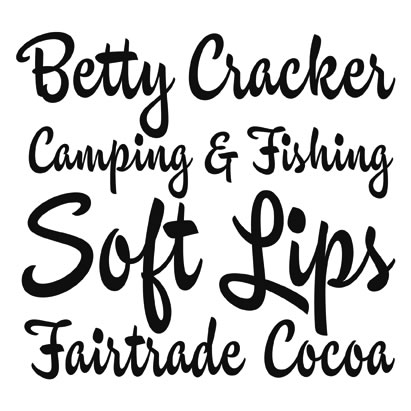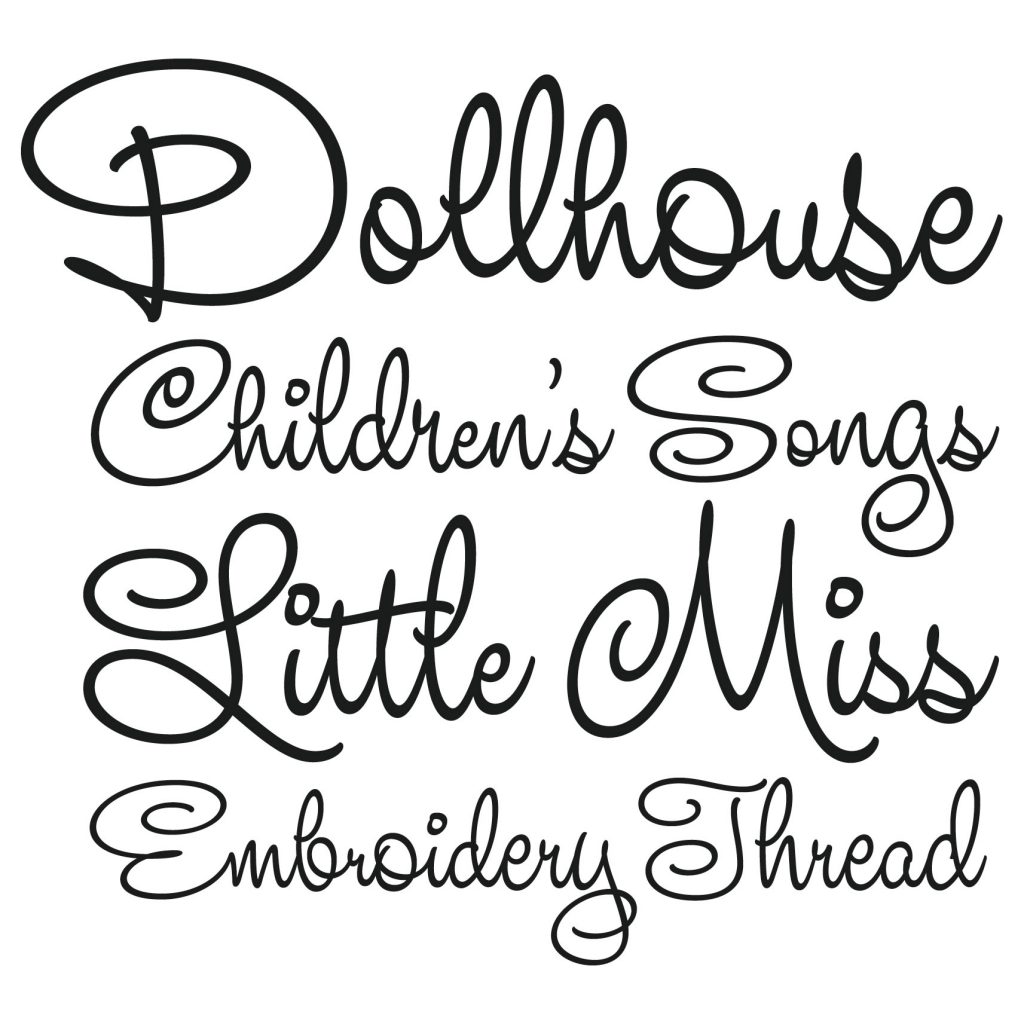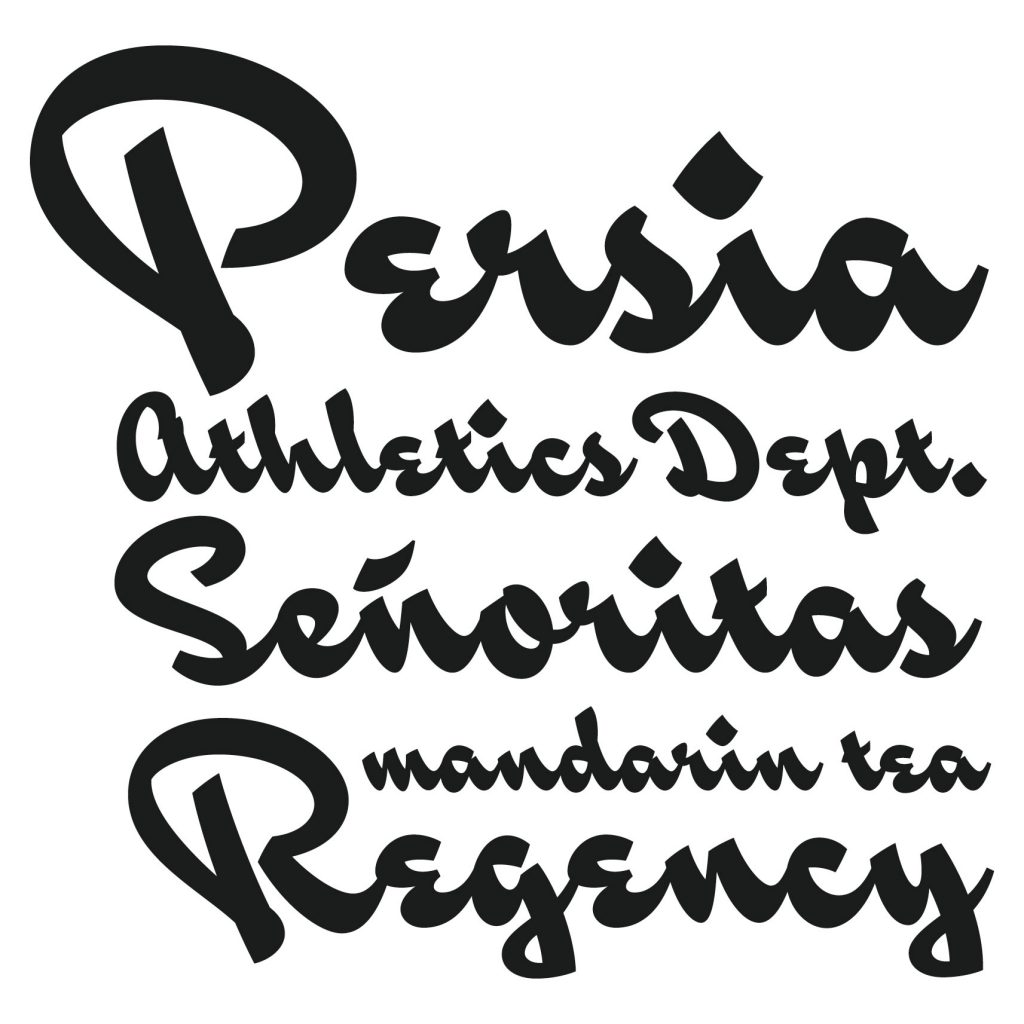
Hablar de House Industries y del impacto que este estudio especializado en el diseño de fuentes ha causado en nuestra profesión, es hablar de una carrera llena de éxitos comerciales y de multitud de premios concedidos por organizaciones, empresas y asociaciones de todo el mundo.
Esta empresa americana, fundada en 1993 por Andy Cruz y Rich Roat como Brand Design Co. en el trastero del apartamento de éste último, supo canalizar de manera muy inteligente su ferviente pasión e influencia hacia la estética gráfica de mediados de siglo XX. Toda una serie de fuentes frescas, divertidas y de una calidad excelente, apoyadas por unos elementos de promoción que hicieron las delicias de todo profesional amante de la tipografía, provocaron con el tiempo, que no hubiera una agencia de publicidad o estudio de diseño que se acabara rindiendo a sus encantos y comprara alguna tipografía diseñada por ellos.
Ken Barber se unió a House Industries en 1996. Su entusiasmo por la caligrafía americana de los años 60 y 70 y su gran capacidad productiva en el diseño y desarrollo de nuevas fuentes, le han convertido en una pieza clave dentro de la empresa.
UnosTiposduros ha hablado con él para conocer un poco más al detalle qué es House y cuál es su particular visión de la tipografía.
¿Me podrías explicar de forma breve quien eres y qué representa House Industries?
House Industries es una fundición tipográfica con base en Delaware (Yorklyn) especializada en el diseño de fuentes digitales, pero también funcionamos y trabajamos como cualquier estudio de diseño gráfico en general. De hecho, además de ser calígrafo y diseñador de tipos, también soy el director de desarrollo tipográfico de la compañía.
¿Cuándo arrancáis un nuevo proyecto, cuál es vuestro proceso de trabajo y a qué le dais mayor importancia?
Cuando empezamos un nuevo proyecto tipográfico, es importante para nosotros considerar varios factores. Primero: el tema del proyecto debe satisfacernos personalmente; esto significa que tanto la base, el guión, como los objetivos del nuevo proyecto debe estimularnos lo suficiente como para justificar el tiempo y el esfuerzo necesarios para producirlo.
Segundo: necesitamos evaluar si nuestros consumidores van a estar o no interesados en nuestras nuevas propuestas tipografías y en todos los productos relacionados. Obviamente, este nuevo proyecto debe diferenciarse claramente de los otros productos que ofrecemos.
Luego empezamos a estudiar y desarrollar las fuentes mientras visualizamos posibles productos que conecten con el tema del proyecto. Después de probar rigurosamente los tipos y los accesorios hacemos material de marketing para hacer publicidad del producto final.
¿Todos los proyectos de House Industries se desarrollan de forma colectiva o bien os gusta trabajar individualmente?
Todos los proyectos de House Industries son producto de un esfuerzo colectivo. Mientras no todo el mundo está involucrado con todos los proyectos particulares, el proceso creativo, sin embargo, sigue siendo muy colaborativo.
Vuestras tipografías respiran una gran admiración por los estilos gráficos de los años 60 y 70. ¿Qué es lo que tanto os apasiona de esa época?
Durante varias décadas pasadas ha habido un declive en el uso del diseño tradicional y en las técnicas de ilustración que generalmente eran usadas durante la mayor parte del siglo XX. Por consiguiente, la artesanía parece ausente en muchos de los diseños gráficos contemporáneos.
House está interesada simplemente en investigar y perpetuar éstas prácticas tradicionales, incorporándolas a nuestro trabajo.
Todos vuestros productos tienen una cuidada presentación gráfica, le dais mucha importancia a los detalles… Y eso también ocurre en todos los materiales promocionales producidos por House (catálogos, vuestro libro, la ropa…)
Trabajar en el diseño de fuentes durante meses puede llegar a ser algo completamente aburrido. Diseñando catálogos que nos comporten ciertas complicaciones o riesgos y presentando soluciones gráficas a esas complicaciones (incluso aplicando esas premisas al diseño de ropa), nos da la oportunidad para escapar de la rutina diaria de puntos y píxeles alrededor de la pantalla de un ordenador.
También es vital para House Industries que cada elemento de todos los proyectos reciba la misma cantidad de atención que nosotros estamos acostumbrados a poner en todos los trabajos.
Y por último, los consumidores, al fin y al cabo, se benefician consiguiendo algo más que una fuente o una camiseta: de hecho, uno de nuestros máximos objetivos es experimentar con el diseño gráfico de forma que el cliente final disfrute de la parte práctica.
Una de las propuestas más interesantes de House Industries es la “tematización” de vuestras tipografías. ¿Como surgió esta idea de no diseñar fuentes de forma independiente sino crear packs con una línea argumental concreta?
Andy Cruz, co-fundador de House Industries, fue el que introdujo la idea de hacer publicidad colectiva con nuestras fuentes a través de embalajes temáticamente relacionados. Anteriomente, la mayoría de los fabricantes de tipos y sus respectivos distribuidores, estuvieron vendiendo fuentes o familias de tipos de forma individual.
Nosotros ampliamos esta idea agrupando fuentes estilísticamente definidas y vendiéndolas como un producto individual.
También, de una manera sutil, se nos presentaba una buena excusa para hacer algún embalaje “cool” y de paso informar a nuestros consumidores sobre artistas y géneros del diseño poco valorados, que de otra manera, ellos nunca hubieran llegado a conocer.
Actualmente hay una proliferación enorme de pequeñas fundiciones gracias a la tecnología digital. Algunas de estas fundiciones tienen una gran calidad en sus trabajos.
¿Sigues o te gusta alguna en concreto?
Personalmente, me alegra mucho ver nuevos diseñadores de tipos y nuevas fundiciones ofreciéndonos diseños de fuentes de calidad.
En nuestro país, desgraciadamente, el pirateo tipográfico está a la orden del día. ¿Cual crees que puede ser la causa y lo más importante, cual podría ser la solución para disminuir este problema?
La solución puede empezar por los diseñadores gráficos profesionales. Los usuarios de las fuentes deberían ofrecer a los diseñadores tipográficos el mismo respeto que esperan para ellos. La piratería no sólo devalúa el diseño de tipos sino que también devalúa el diseño gráfico en general. Debido a esto, ha provocado que el diseñador gráfico pierda respeto por parte del público no profesional y a consecuencia de ello, prácticamente todo el mundo tenga una imagen mas o menos distorsionada de lo que es actualmente un diseñador gráfico. Nosotros, como profesionales, debemos trabajar para promover y cuidar ese respeto.
Creo que esta base puede ser un ejemplo para el público en general y puede servir para que haya un cambio de actitud tanto para el diseñador gráfico como para los profesiones de diseño de tipos.
Vuestro nuevo proyecto se llama Studio Lettering. ¿Puedes hablarme un poco de él?
Studio Lettering comprende una colección de tres tipos de letras de estilo Script y una fuente de símbolos inspirada en la publicidad caligráfica de mitad del siglo XX. Estas tipografías exploran los diferentes matices estilísticos característicos de la época que las hacen particulares en ciertos lenguajes y culturas.
Las características “coloquiales” de estos diseños tipográficos las hacen diferentes entre sí, y los diversos cambios diacríticos dependen del lenguaje escogido.
Las fuentes de Studio Lettering se diseñaron basándonos en el estudio de diferentes libros de escritura, por observaciones históricas y en mis conversaciones con calígrafos y especialistas lingüísticos.
Estas fuentes también hacen un uso extensivo de la tecnología OpenType para conseguir los efectos de la forma y el movimiento de la caligrafía tradicional. El objetivo en la programación de las fuentes no es repetir la apariencia manual; es más un intento para encontrar terrenos comunes entre los procesos de caligrafía y el diseño de tipos contemporáneos.
¿Cuál crees que ha sido el secreto de vuestro éxito?
Yo pienso que el trabajo duro, una mente abierta y una buena predisposición para tomar riesgos pueden ser atribuidos a cualquier éxito que haya tenido House Industries.
¿Cuáles son vuestros proyectos futuros? (tipograficamente hablando, claro)
En breve House Industries estrenará la colección de fuentes de Alexander Girard y productos relacionados, inspirados por el trabajo del último diseño del icono americano.